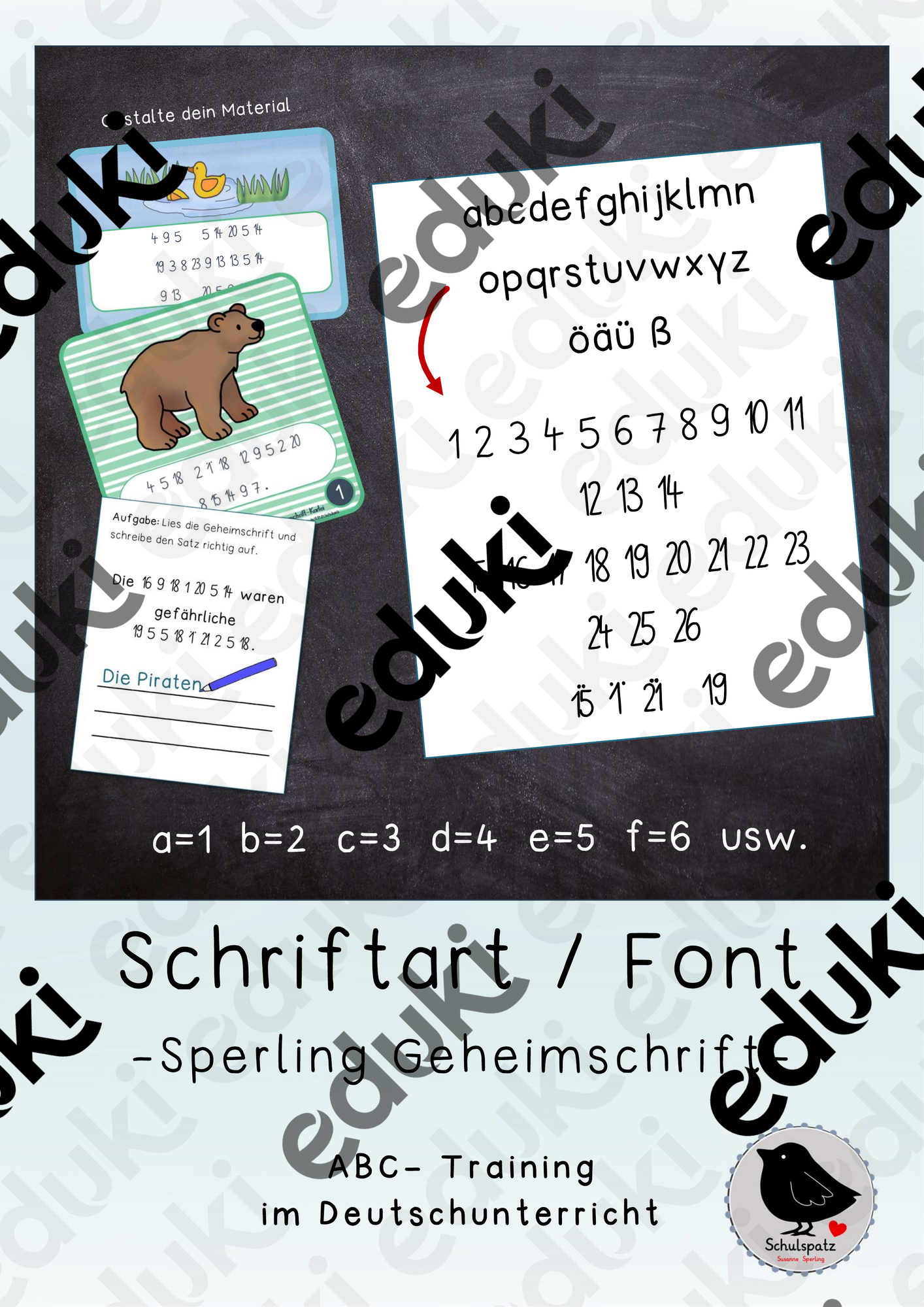
3. Geheimschrift
Mit idieser tollen Schrift kannst du viele verschiedene Rätsel zum ABC erstellen. Jeder Kleinbuchstabe ist mit einer passenden Ziffer belegt (a=1, b=2 etc.). Nach der Installation der Schriftart kannst du beliebige Wörter oder Sätze schreiben, Karteikarten oder Arbeitsblätter gestalten, diese dann markieren und mit einem Klick (Schriftart „Sperling Geheimschrift“ auswählen) in einen Zahlencode umwandeln. Diesen müssen die Kinder dann entschlüsseln und erhalten ein Lösungswort. Dabei wiederholen sie automatisch und ganz spielerisch das ABC. Tipp: Ideal für das Erstellen von ABC-Karteien für den Deutschunterricht.Die Schrift darf auch für kommerzielle Zwecke genutzt werden, sofern du die Quelle angibst (Schriftart Sperling Geheimschrift, Schulspatz).Viel Freude beim kreativen Gestalten deiner Materialien...